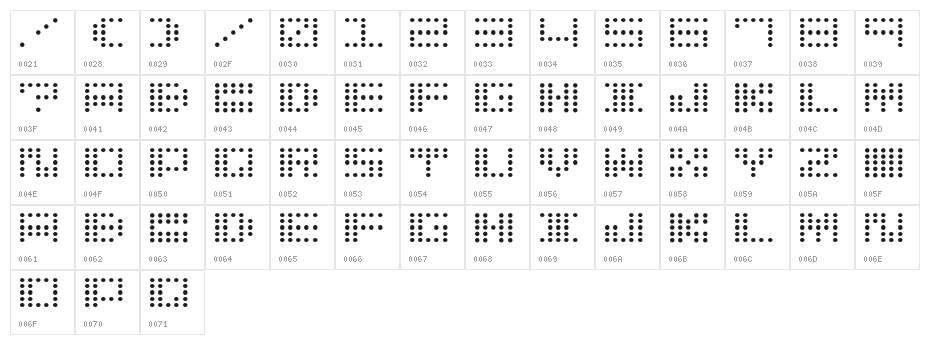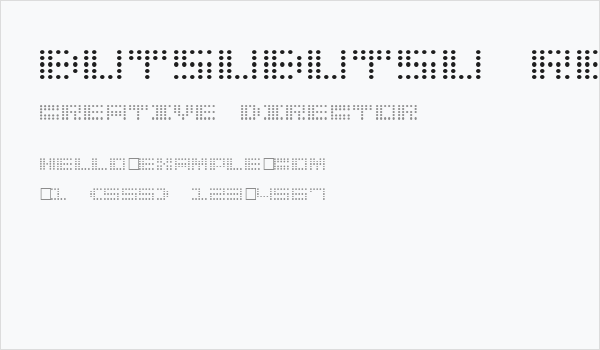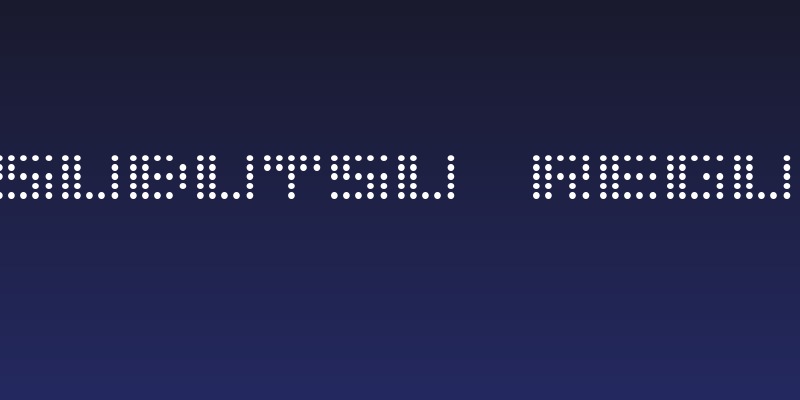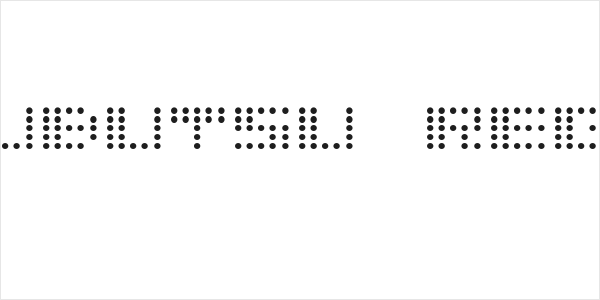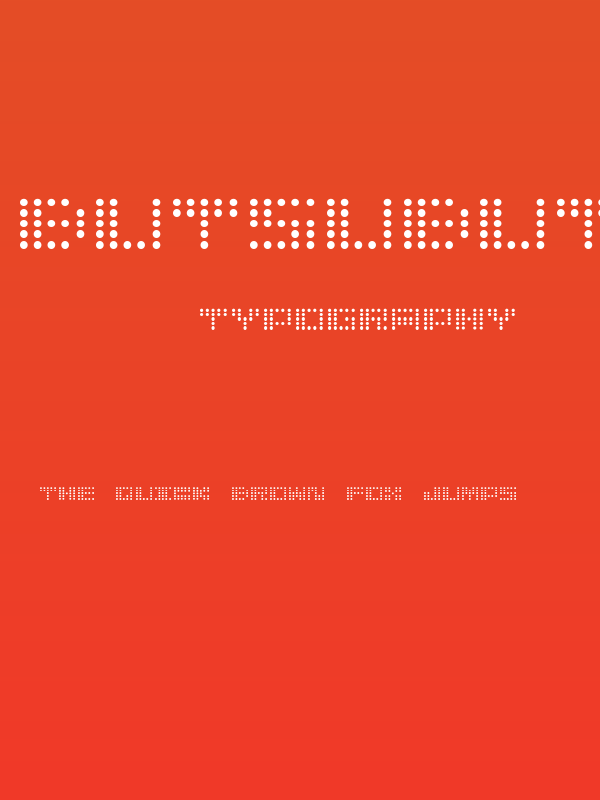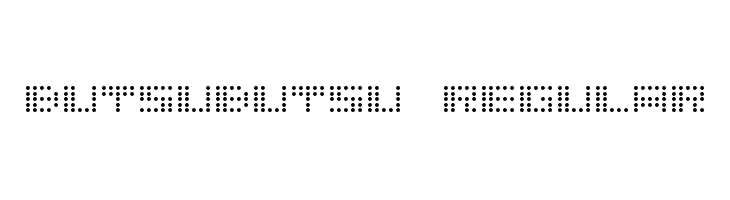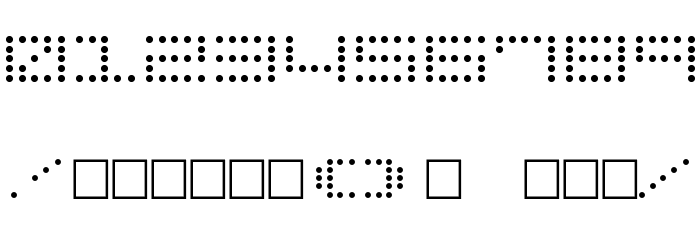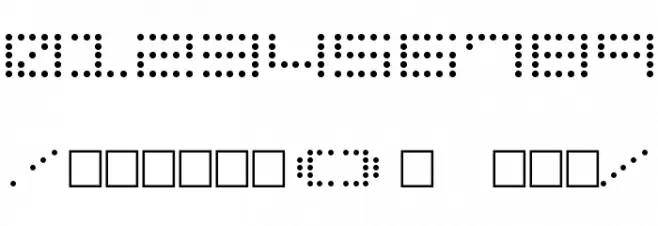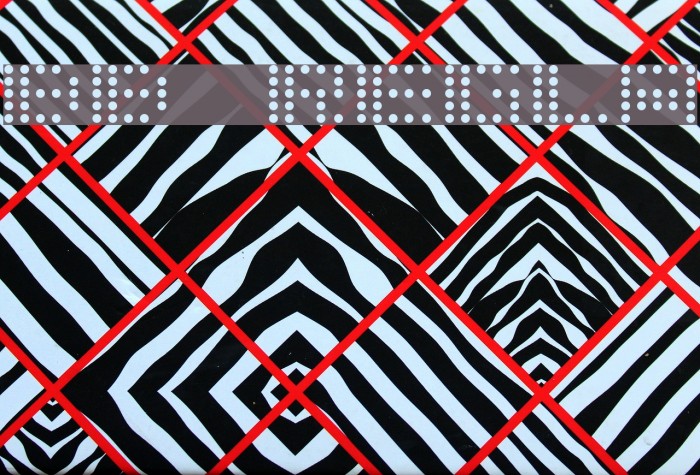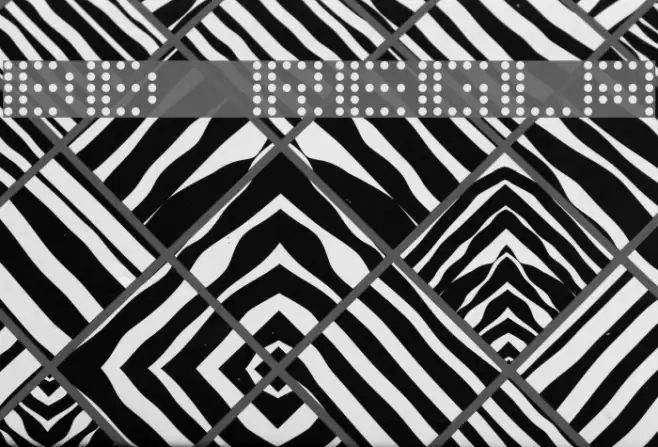
Butsubutsu Regular Font
| Nom | Butsubutsu Regular |
| Catégories | Dotted |
| Style général | Retro, Modern |
| Cas d'utilisation | Logos, Headlines, Digital Art |
| Projets proposés | Ideal for digital art, retro-themed designs, tech-related branding, and creative posters. |